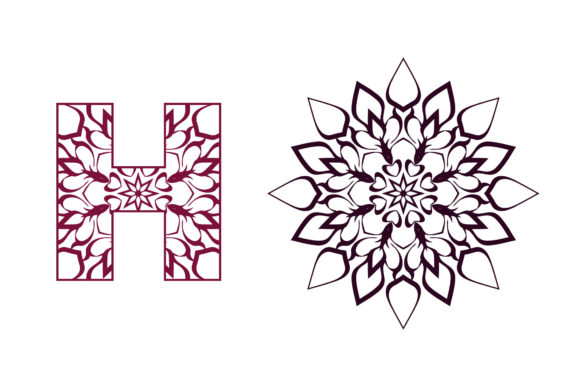
Mandala Font Alphabet H Ornament
適切なデザイン要素を見つけるのは難しい場合がありますが、Mandala Font Alphabet H Ornamentは作品を即座に引き立てる優れたコレクションを提供します。
POD(オンデマンド印刷)製品、結婚式の招待状、またはソーシャルメディアのグラフィックを作成している場合でも、Mandala Font Alphabet H Ornamentは理想的です。